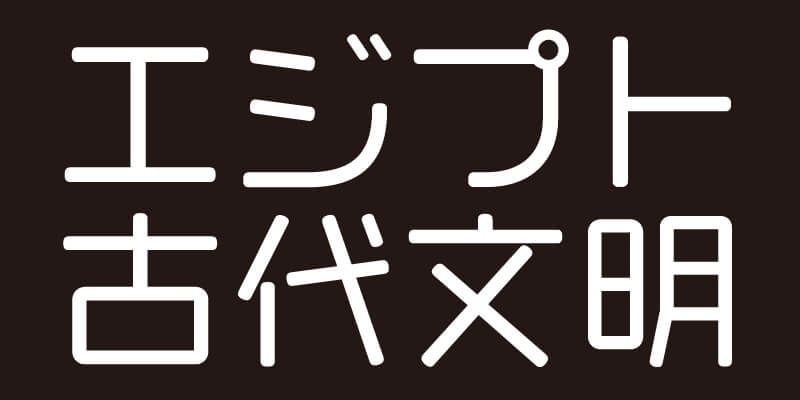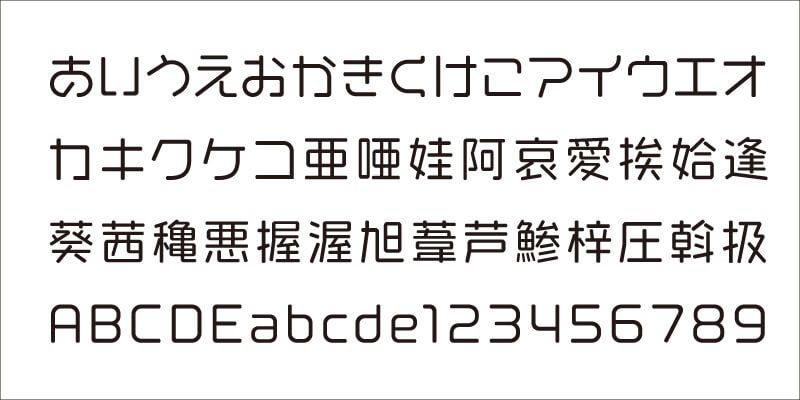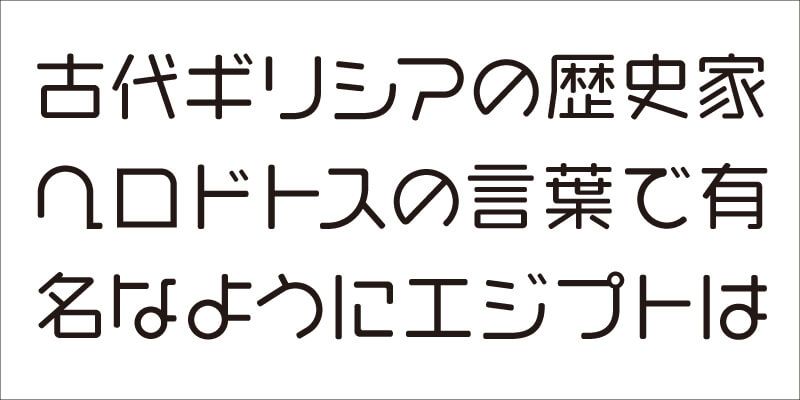
VDL-GigaMaruJr est basé sur le style libre de VDL-LogoJr, mais il s’agit d’une police de style gothique (sans empattement) arrondie, avec des bords et des extrémités de traits arrondis. Ses courbes douces et lisses créent une ambiance décontractée.